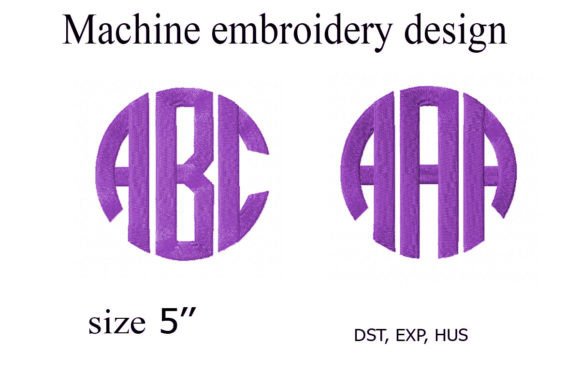
Circle Monogram Embroidery Design
適切なデザイン要素を見つけるのは難しい場合がありますが、Circle Monogram Embroidery Designは作品を即座に引き立てる優れたコレクションを提供します。
POD(オンデマンド印刷)製品、結婚式の招待状、またはソーシャルメディアのグラフィックを作成している場合でも、Circle Monogram Embroidery Designは理想的です。